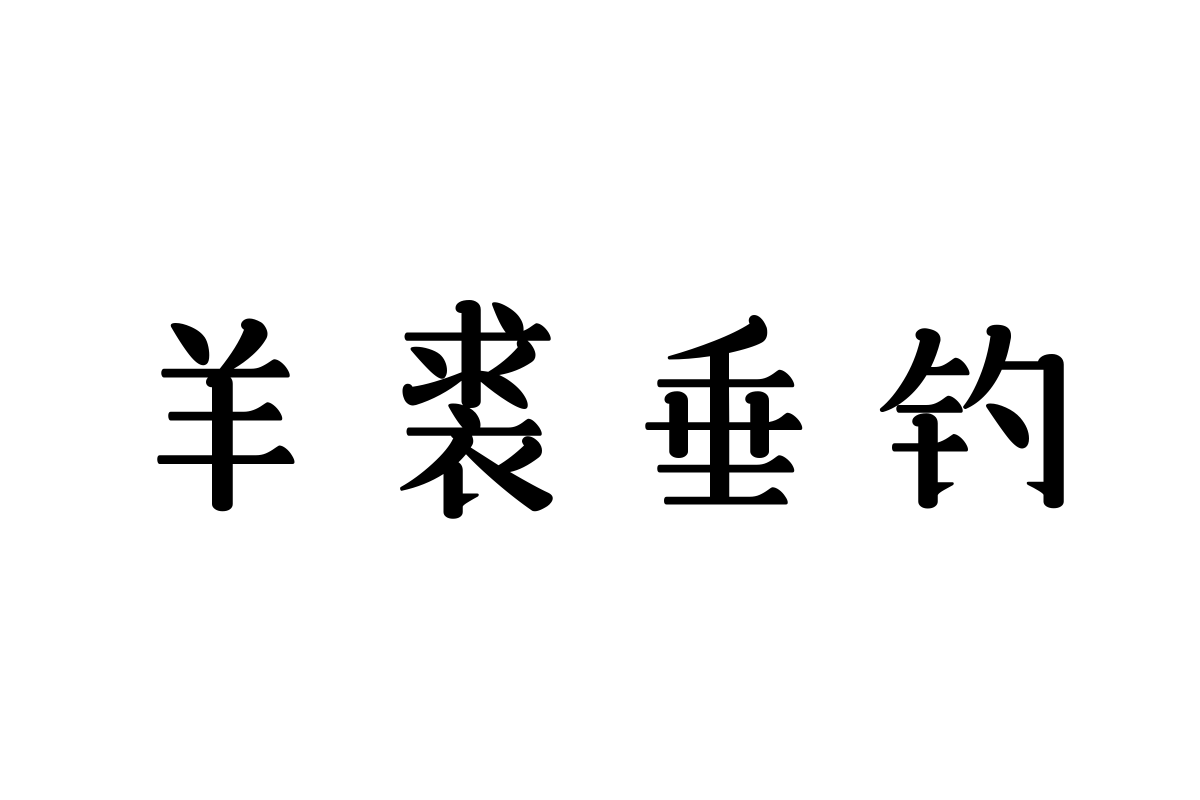
三极悠闲宋字体是一种具有现代感和艺术性的中文字体,由设计师精心打造。这款字体以其独特的字形设计和优雅的线条流畅度而受到广泛好评。它适合用于各种需要展示文字美感的场合,如广告设计、网页设计、书籍出版等。
三极悠闲宋字体的特点如下:
1. 字形优美:三极悠闲宋字体采用了简洁的线条和柔和的曲线,使得文字看起来既美观又易于阅读。
2. 风格独特:这款字体的设计灵感来自中国传统文化中的山水画,因此它具有独特的东方韵味。
3. 适应性强:三极悠闲宋字体适用于多种场景,无论是在网页设计还是印刷品中都能展现出其独特的魅力。
总之,三极悠闲宋字体是一款非常实用且具有艺术气息的中文字体,适用于各种需要展示文字美感的场合。